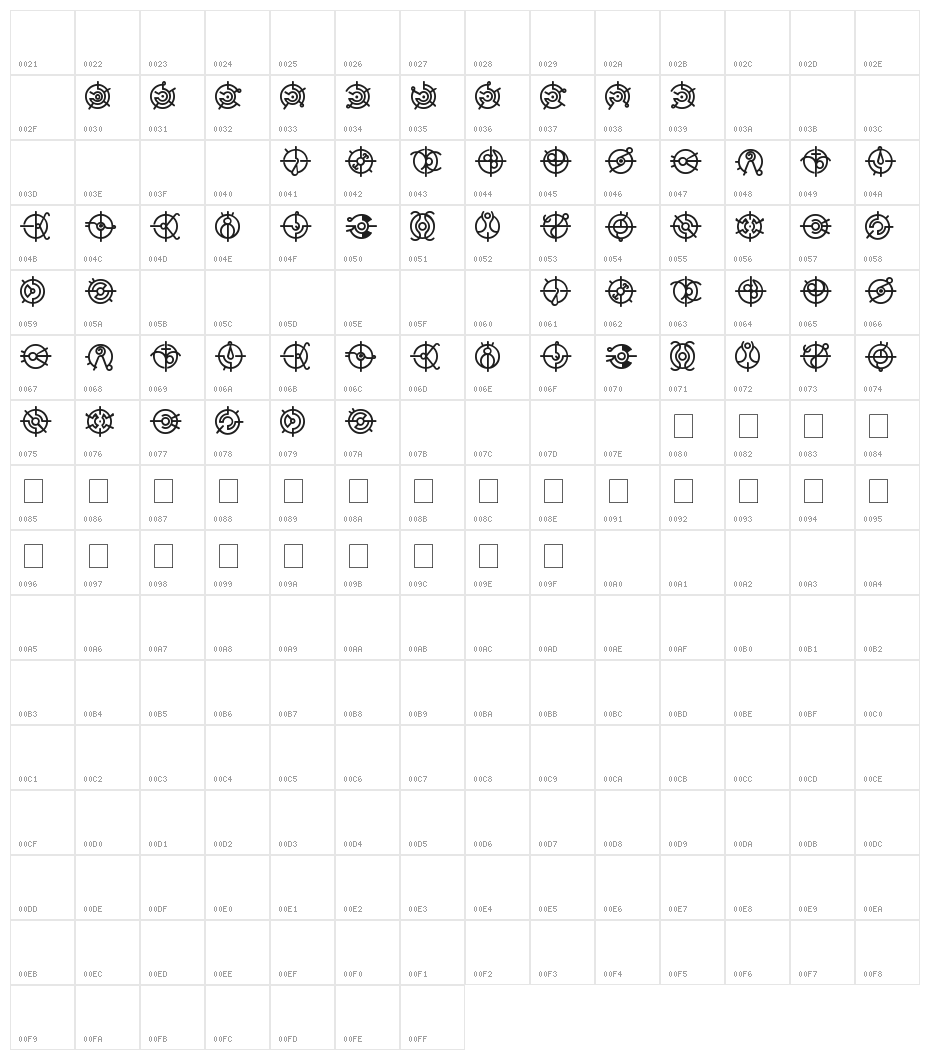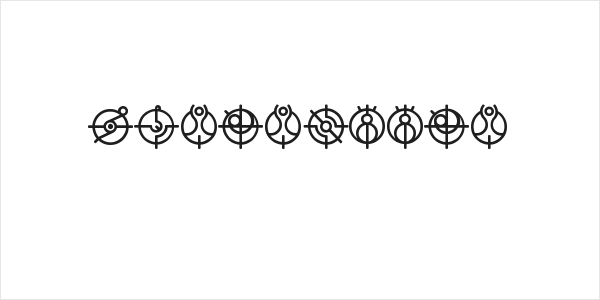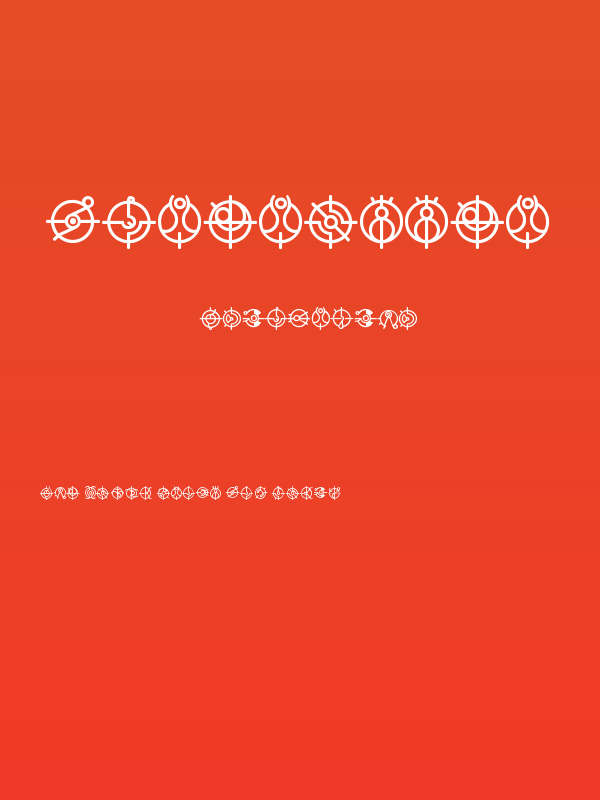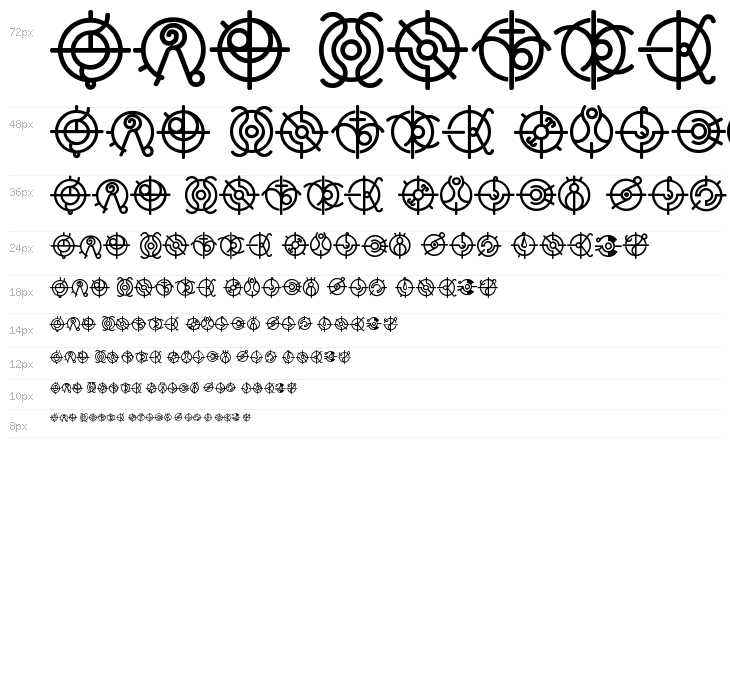
Forerunner Font
| النمط العام | Futuristic, Abstract, Decorative |
| حالة الاستخدام | Logos, Posters, Titles, Themed Events |
| مشاريع مقترحة | Ideal for sci-fi themed designs, video game interfaces, movie posters, or any project needing a mysterious, futuristic touch. |